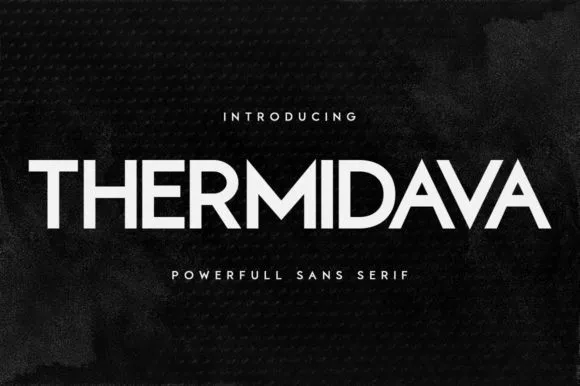
Thermidava Font Family – Fonte Grátis
Thermidava Font Family
A Thermidava Font Family é uma refinada sans-serif com alta contraste que se destaca perfeitamente para as demandas modernas e contemporâneas. Desenvolvida sobretudo pensando na simplicidade visual, ela oferece um ar de modernidade e distinção a qualquer projeto em que seja aplicada. Suas linhas finas e claras destacam-se ainda mais ao serem contrastadas com suas linhas grossas e fortes, criando uma sensação de movimento e agilidade que se alinha perfeitamente para a dinâmica da atualidade. Se você busca um estilo de fonte que possa complementar os seus ideais criativos em qualquer contexto gráfico, esta Thermidava pode ser o elemento adicional necessário para tornar sua ideia ainda mais inovadora e chamativa. Aproveite!